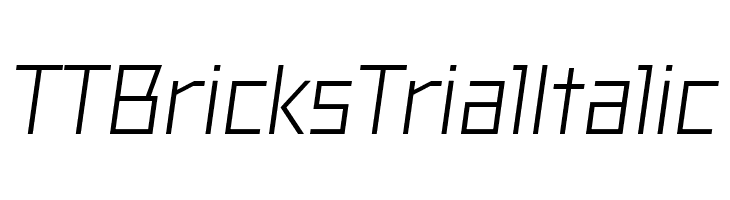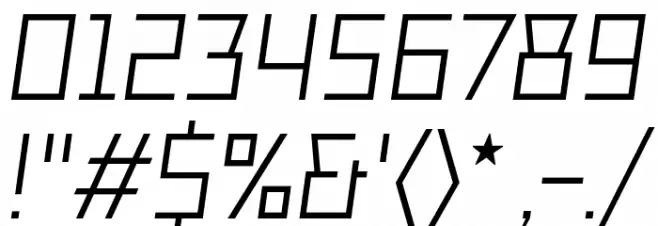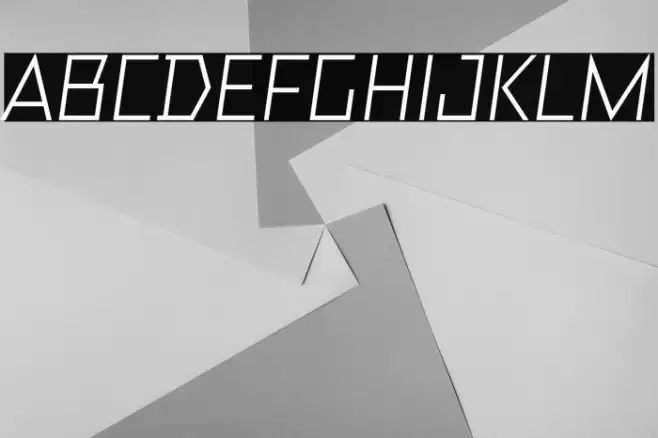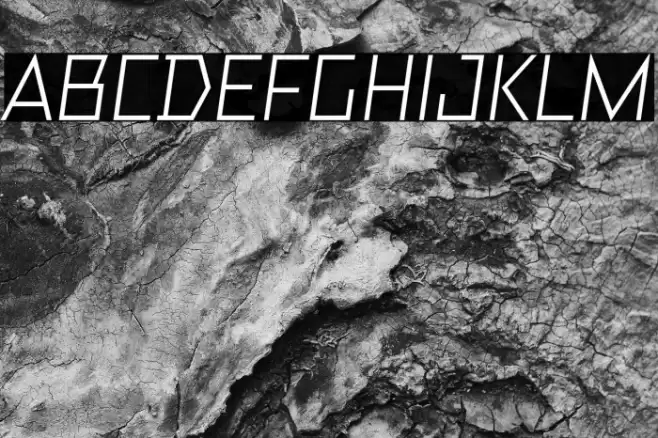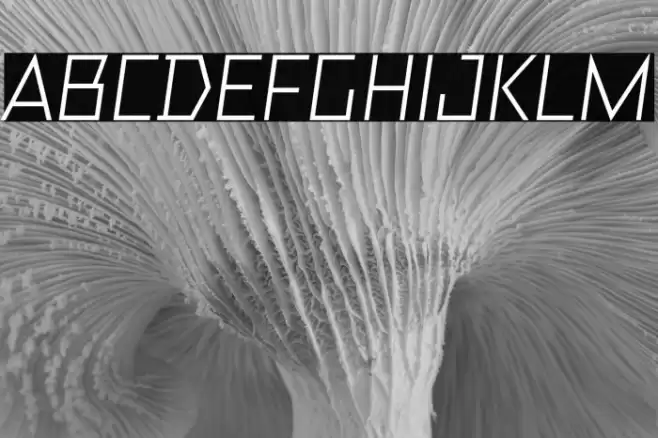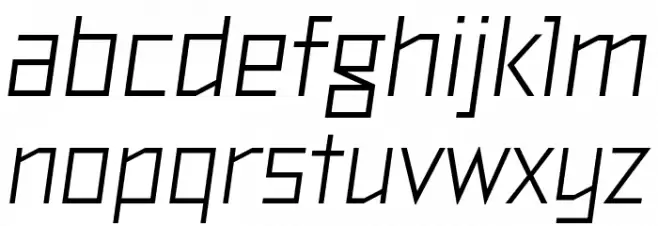
TT Bricks Trial Italic Font
| Caz de utilizare | Headlines, Logos, Digital interfaces |
| Proiecte propuse | Ideal for tech branding, modern advertising, digital interfaces, and editorial design. |